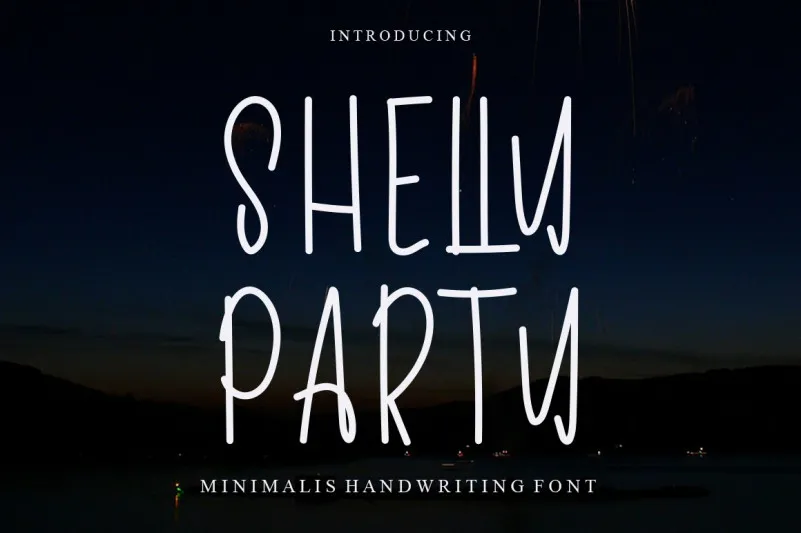
Shelly Party Font – Download Grátis
A fonte ‘Shelly Party Font’ é uma escolha elegante para quem busca uma mão-dura e charmosa escrita a mão. Este estilo delicado e divertido certamente se destacará em designs variados, tornando-os ainda mais únicos e chamativos. Perfeita tanto para anúncios de eventos festivos quanto para criação de design editorial personalizado, ela é perfeitamente adaptável à criação de identidades digitais, cartazes publicitários ou até mesmo adesivos de carro. Este font representa a amizade, alegria e romance em cada letra que você escrever. A Shelly Party Font é um convite para criar uma atmosfera festiva em qualquer projeto onde ela for usada.